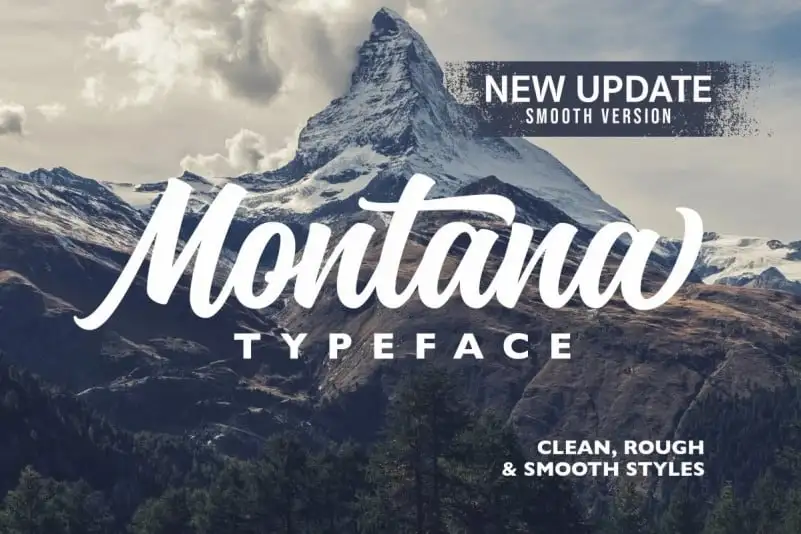
Montana Script Font – Download Grátis
A Montana Script Font é uma fonte casual que combina elementos do estilo de letras manuscritas para criar um toque de escrita à mão, dando ao tipo uma aparência personalizada. Com seus traços fluidos e elegantes, esta fonte é perfeita tanto para design gráfico quanto para artesanato. É especialmente ideal para uso em logomarcas, insígnias, embalagens, cartazes, carteiras ou camisetas, bem como cartas de cumprimentos e convites de casamento. A Montana Script Font também pode ser utilizada com a combinação de caracteres alternativos que complementam o estilo elegante desta fonte. Suas formas fluidas permitem criar mensagens atrativas, tornando-a uma escolha versátil para diversos tipos de projetos gráficos e criativos. Ideal tanto para designers profissionais quanto para entusiastas do design, a Montana Script Font é perfeita para aqueles que desejam um toque único no seu próximo projeto visual.